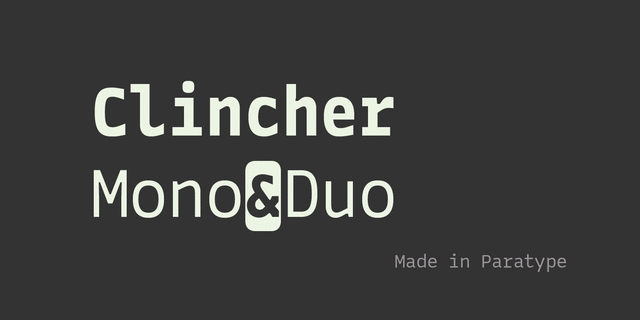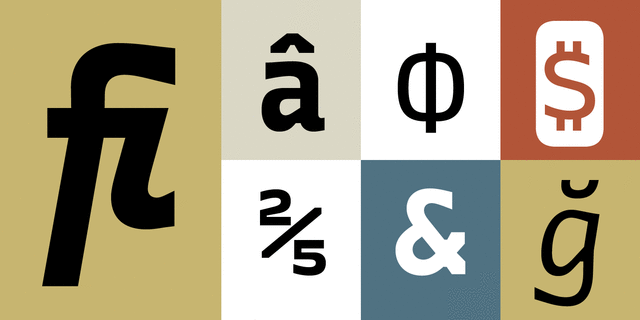
Clincher — система начертаний, спроектированных специально для работы с программным кодом и решения задач, связанных с созданием пользовательских интерфейсов. Характерный рисунок знаков и наличие альтернатив позволяют использовать Clincher в акциденции, навигационных проектах и вёрстке небольших объемов текста, требующих эффекта регулярности и моноширинности. Четыре дополнительных набора моноширинных начертаний, а также начертания, использующие две базовые ширины кегельной площадки, позволяют варьировать плотность набора текста. Шрифт разработан Александром Любовенко и выпущен компанией Paratype в 2018 году.
строгий, элементарный, ломаный, угловатый, точный, ровный, прямоугольный, стабильный, статичный, простой, логичный, прагматичный, практичный, твердый, лаконичный, доступный, серьезный, железный, стальной, устойчивый, автоматический, искусственный, холодный, машинный, инженерный, индустриальный, техногенный, стандартный, городской, резкий, четкий, острый, чертежный, компьютерный, урбанистический, понятный, космополитичный, прямой, современный, глобализированный, глобалистичный, офисный, оригинальный, тесный, убедительный, сильный, жесткий, заметный, броский, грубый
техника, код, чертеж, конструктор, инженер, автоматика, ГОСТ, город, навигация, наука, дизайн, IT, айтишник, компьютер, электроника, программирование, айти, технологии, железо, промышленность, офис, бухгалтер, коворкинг, игра, робот, рентген, хакер, станок, инструмент, тренажеры, компьютерная игра Стилистика: